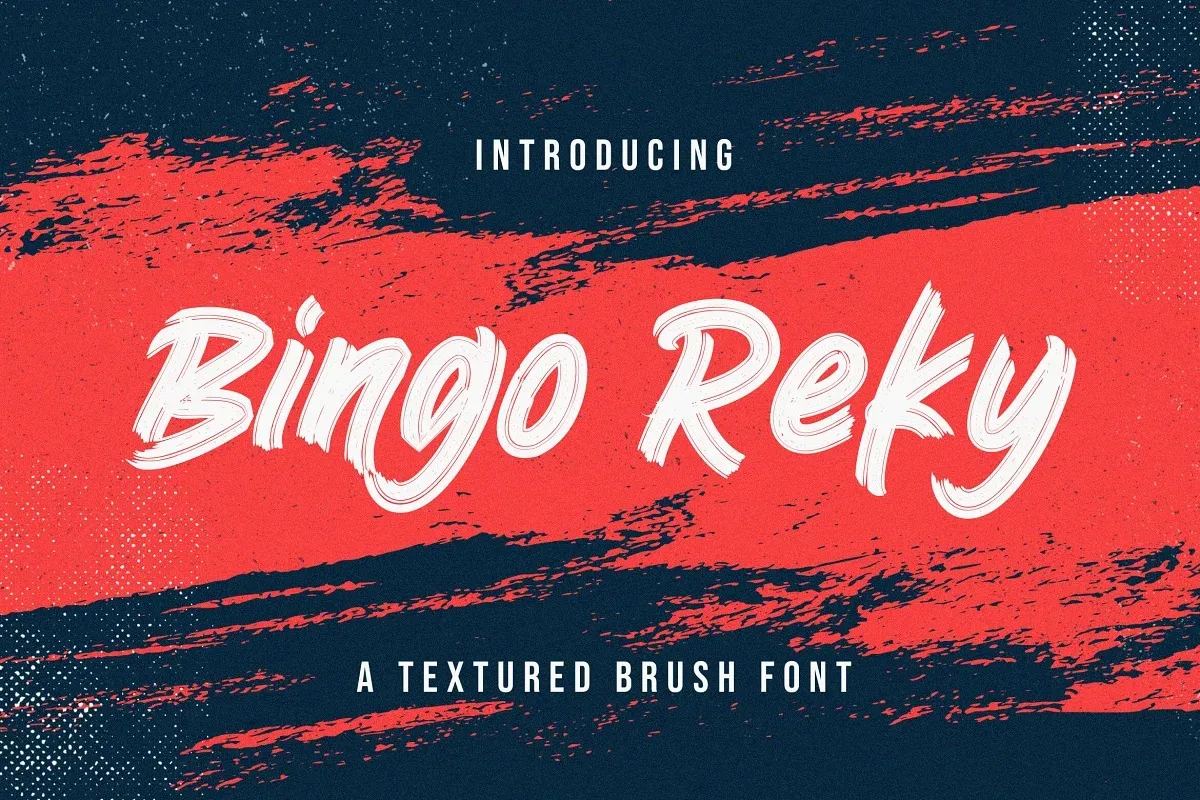
A Bingo Reky Font é uma nova e fresca fonte círconfusa com estilo de esfregador manual, perfeita para diversificar sua identidade visual. Com um ar natural que parece ser pleno do momento atual, esta elegante tipografia atende a uma ampla gama de necessidades. Ideal tanto para criar logotipos profissionais quanto designs de produtos, etiquetas e até mesmo posts em redes sociais, essa fonte é ideal para aqueles que procuram um toque autêntico de escrita à mão, seja para criações de convites, adesivos ou materiais para uso no ambiente corporativo. Além disso, a Bingo Reky Font também será uma excelente escolha para qualquer tipo de conteúdo em signboard, desde avisos informativos até design esportivo ou marcação de eventos especiais. Se você está buscando um elemento que dê vida à sua criação e lhe permita explorar os bordais da criatividade, a Bingo Reky Font é uma escolha perfeita. Seja para criar designs personalizados para o seu site, impressão ou até mesmo para adicionar um toque único em qualquer arte digital que você deseje desenvolver. Engane-se se pensar que esta fonte círconfusa é apenas uma ferramenta profissional – ela também pode ser usada para dar um tom autêntico e singular a sua marca, seja qual for o seu campo de atuação.